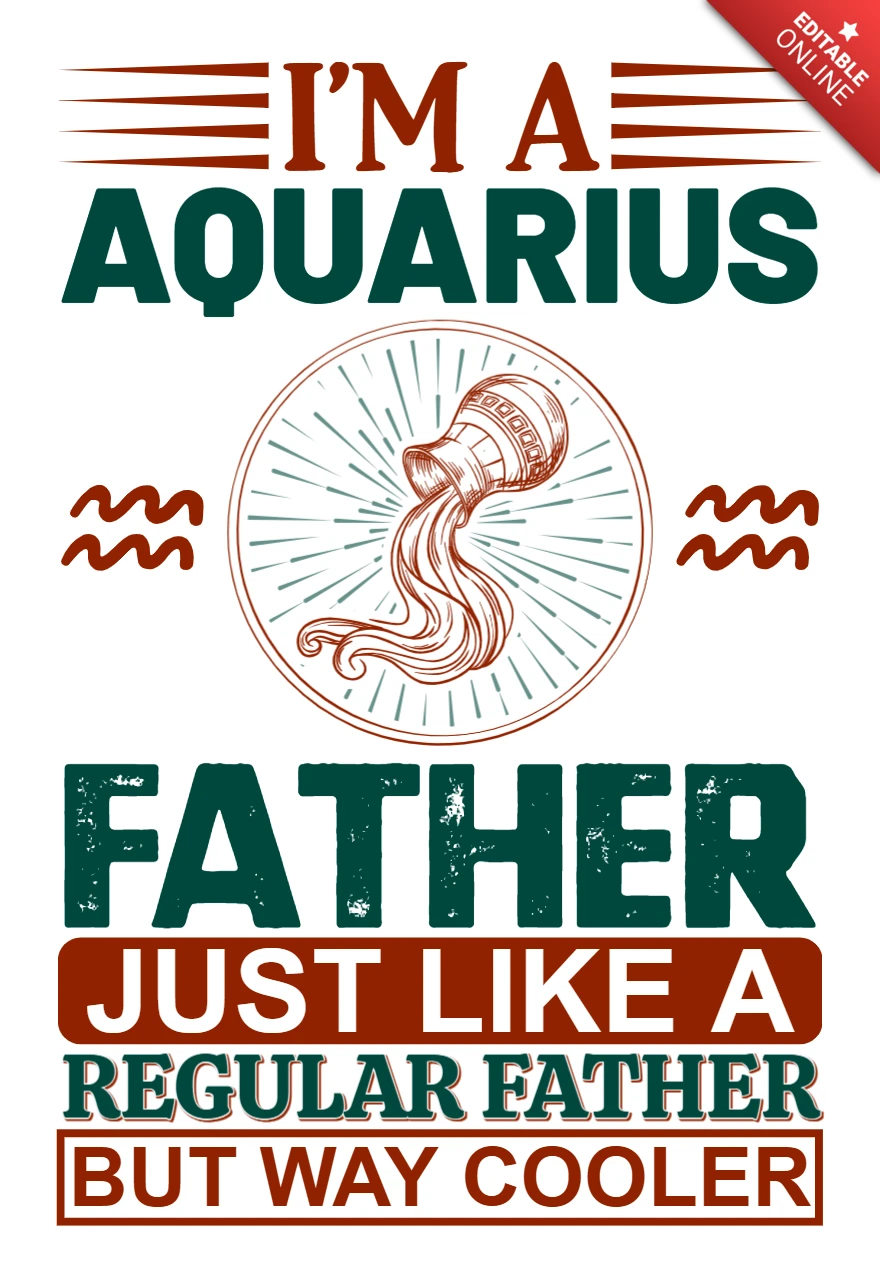
Bewerkbaar retro typografie ontwerpsjabloon voor aquarius vaders
Bewerken in Design Studio Downloaden in JPGMaak een humoristisch, bewerkbaar postersjabloon voor vaders van de Waterman met retro typografie, perfect voor unieke cadeaus die hun astrologische charme en opvoedingsstijl laten zien.